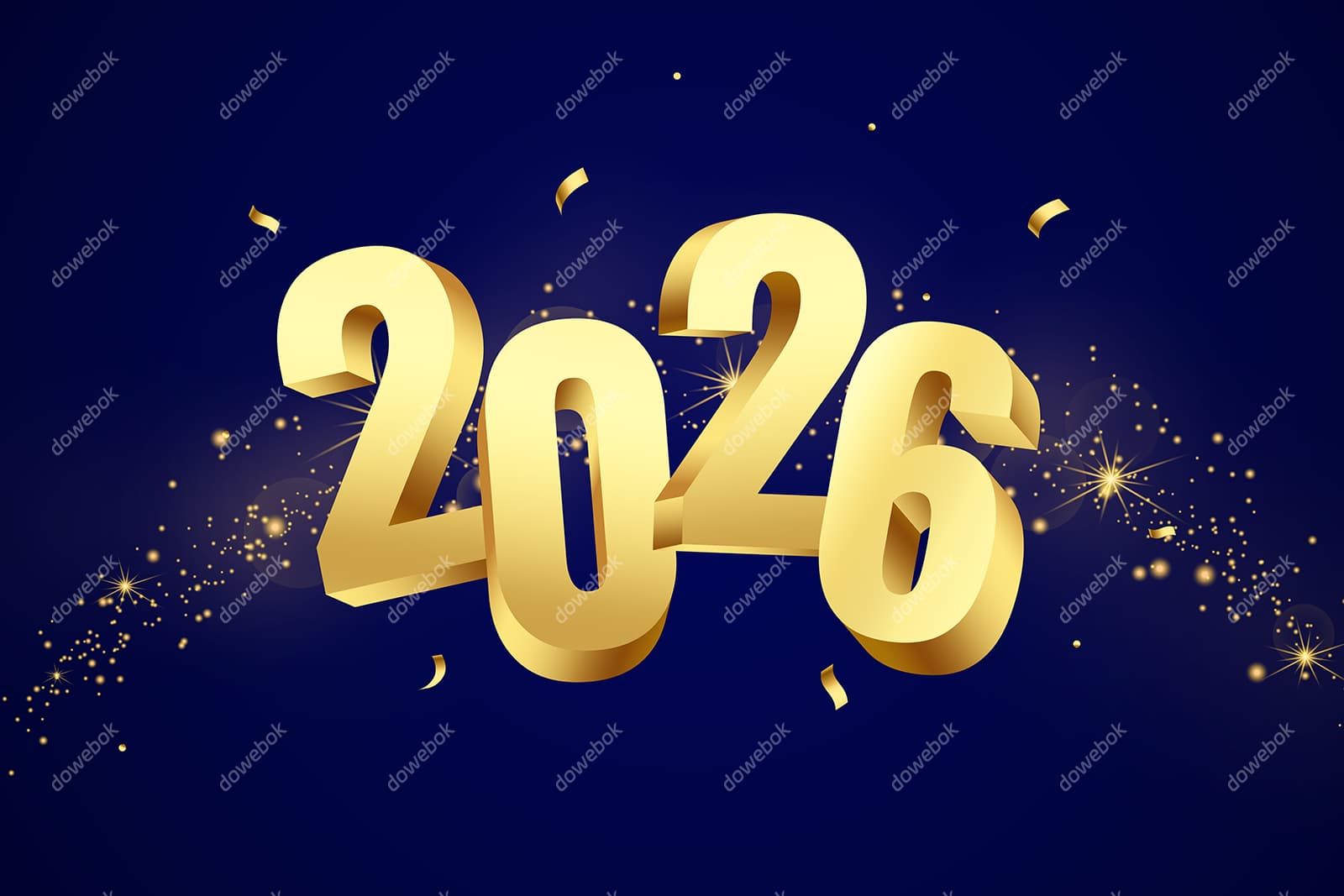
这是一款立体金色数字设计的 2026 新年快乐矢量素材,深邃藏蓝背景上,立体金色 “2026” 字体质感华贵,光泽饱满。数字周围环绕着金色星芒与飘带装饰,营造出璀璨灵动的氛围。整体黑金色调高级大气,立体字与星光元素既传递出新年的热烈喜庆,又以精致质感凸显奢华仪式感,适配高端新年贺卡、活动宣传等场景。